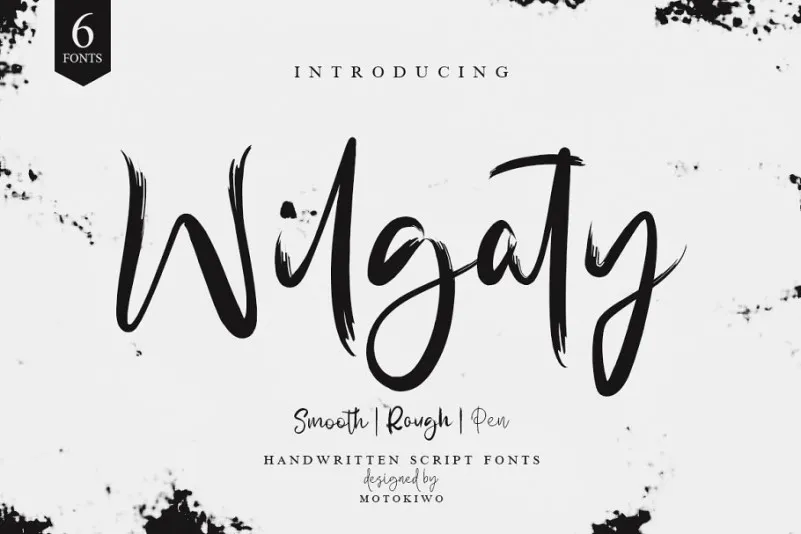
Wilgaty Brush Font – Download Grátis
Esta é uma fonte brush que foi cuidadosamente criada para dar vida nova a seus designs! Ideal para estampar na mídia social das suas empresas ou usar em logotipos, Wilgaty Brush Font promete revolucionar seu visual de design. Motokiwo, o designer responsável pela criação e compartilhamento desta fonte, apresenta-nos Wilgaty Font. Esse é um tipo de script que está embasado na escrita a mão, mas com três variações de traçados únicos. A Wilgaty Brush tem uma personalidade vivaz e encantadora, especialmente perfeita para projetos de design que buscam manter a mesma linha de estilo mas com um visual diferente. Seja para criar logos icônicos ou montar as postagens nas redes sociais da sua empresa, esta fonte é versátil o suficiente para atender a uma variedade ampla de trabalhos de design. Se você estiver procurando por uma maneira de dar um toque único a seus projetos sem perder a essência do seu trabalho, então Wilgaty Brush será uma escolha ótima. Wilgaty está disponível em três variações de traçado e é perfeitamente adaptável aos mais diversos tipos de projetos de design. O designer Hamilton criou esta fonte com o objetivo de fazer dela uma ferramenta indispensável para qualquer designer gráfico, seja profissional ou iniciante. Por isso, ela é um recurso valioso que irá tornar seus designs ainda mais atraentes e distintivos.